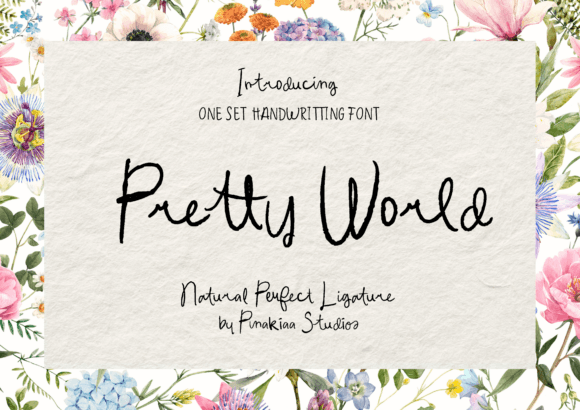
Pretty World
適切なデザイン要素を見つけるのは難しい場合がありますが、Pretty Worldは作品を即座に引き立てる優れたコレクションを提供します。
POD(オンデマンド印刷)製品、結婚式の招待状、またはソーシャルメディアのグラフィックを作成している場合でも、Pretty Worldは理想的です。